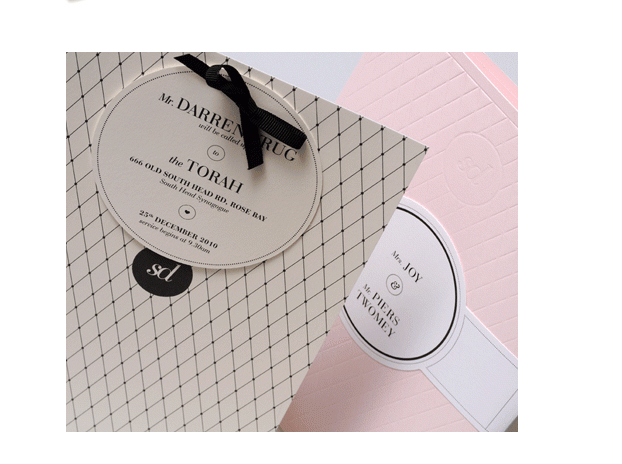
Antiqua für Hochzeitseinladung
Ich bin mal in eigener Sache unterwegs, ich möchte unsere Hochzeitseinladung optisch an die Karte anlehnen,die ich als Screenshot angehängt habe. Ich habe die Dame, die die Karte gestaltet hat schon angeschrieben, ob sie mir den Font verrät, aber ich schaue auch noch nach Alternativen.
Ich bin also auf der Suche nach einer schönen klassizistischen Antiqua mit einem ansprechenden & -Zeichen und stark variierender Strichstärke.
Habt ihr Vorschläge?  :-)
Nicht gerade klassizistisch – aber fast und wie ich finde sehr schön umgesetzt:
... und dieses & ist ja eigentlich auch nicht klassizistisch, oder?!
Ein weniger geschwungenes & dafür aber klassizistischer und dennoch recht ›warm‹ von der Anmutung:
Wie wäre es mit der Didot von Hoefler & Co.? Bei dieser stehen dir verschiedene optische Grade zur Verfügung.
Die Baskerville hat auf jeden Fall ein entzückendes & - die käme theoretisch in Frage
-Schade, dass wir kein Q im Text haben, das ist ja auch ein Augenschmaus!
Das einzige, was mir hier fehlt,ist das geschwungene R, davon gibts nämlich einige im Text und das fand ich auf der Beispielkarte so schön feminin.
Prinzipiell schön, hier stimmt auch das R - dafür aber die nicht ganz perfekte Variante des &-Zeichens.
Am schönsten wäre natürlich eine Schrift, die beides hat *nadelimheuhaufensuch*
Aria? Auch wenn diese ebenso eher vom klassizistischen Formprinzip abweicht, könnte sie etwas für den Anlass sein.
Auch schön:
Du solltest Dir ruhig mal die gesamte Glyphentabelle ansehen. Da sind bei allen auch interessante Alternativen und Schwungbuchstaben enthalten.
Ohhh Robert, jetzt hab ich aber die Qual der Wahl, Klassizismus hin oder her, die sind ja superschön! Danke! Und bei der umfangreichen Glyphensammlung juckt es mich ja jetzt schon in den Fingern :)
Das mit der Mischung hatte ich mich auch schon gefragt...
Jetzt werd ich aber in Ruhe ein bißchen zwischen Santis und Aria hin und herklicken und mich hoffentlich irgendwann entscheiden können :D
Ich glaube allerdings, dass ich mich schon verliebt hab in die Aria...oder in die Santis...oder in alle Beide...Verdammt :)
Für die Aria spräche die mögliche Erweiterung durch eine passende Textschrift mit optischen Größen – auch ein Leckerbissen und vor allem eine Qualitätsschrift ;-):
Bei der Santis begeistern mich die filigranen Schwünge und zahlreichen Varianten. Und man könnte sie schön mit der serifenlosen Andes (auch von Latinotype) kombinieren.
(Obwohl die auch gut zur Aria passen würde …)
Hehe, in der Tat nicht ganz einfach die Entscheidung. ;-)
@Robert, jetzt machst du es mir aber auch nicht leichter :D
Die filigranen Elemente der Santis sind natürlich für so eine Einladungskarte ( und dann später die Menukarten, Trauungsablauf-Heftchen, Platzkarten usw) eine wirklich schöne, passende Sache, mit der man viel spielen kann....Die Aria hat mich halt aber auch vom ersten Klick weg begeistert.
Egal für was ich mich entscheide, die Kombi mit der Andes ist eine super Empfehlung, Danke!
Die Dolly mag ich prinzipiell sehr gerne, für meinen Geschmack ist sie für diesen Fall nur nicht ganz so zart und elegant wie die Aria & Santis.
Dann feiere doch den Quantensprung in der Beziehung, ihre neue Qualität – oder setz ein Gericht mit Quitten (edel, sollten durchaus hochzeitstauglich sein) aufs Menü! :party:
Spaß beiseite: die Schriftempfehlungen überlasse ich den Gurus. Ich lese aber höchst inspiriert mit. Die nächste Hochzeit kommt bestimmt!
Na dann hat sich das mit der hochzeit ja eh erledigt.
Thaha, gute Ideen :D  Oder eine Quarkspeise zum Dessert  :-D
Danke für die Vorschußlorbeeren Robert, die Strichstärke habe ich natürlich im Blick  :-D
Das gekreuzte W und der kurze Stamm vom G sind charakteristisch für die Bauer Bodoni, die ITC Bodoni und deren Nachahmungen bzw. die Bodoni-Versionen die sich auf die gleichen Vorlagen beziehen. Bodoni selbst hat schon mehrere verschiedene ‘Bodonis’ herausgebracht. Mal strenger, mal weniger streng (aber niemals konstruiert, das ist ein Märchen aus dem 19. Jahrhundert). Das schnörkelige & gibt es entweder als Alternate, eventuell auch in einer der italic-Schnitte, oder es kommt aus einer anderen Schrift.